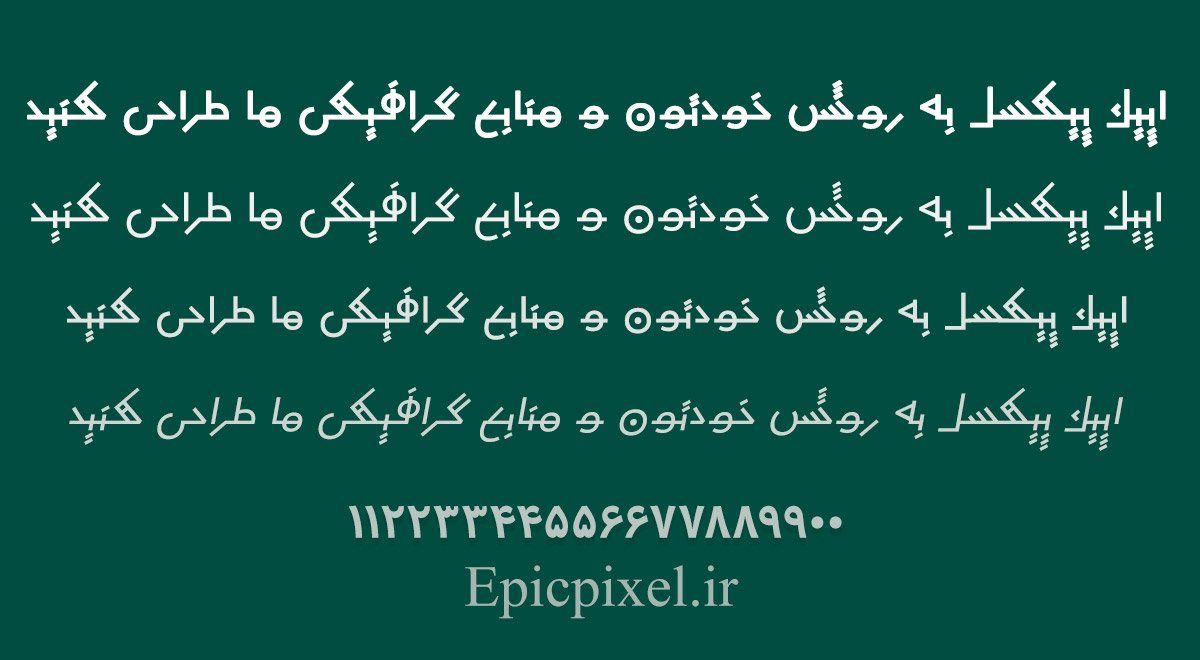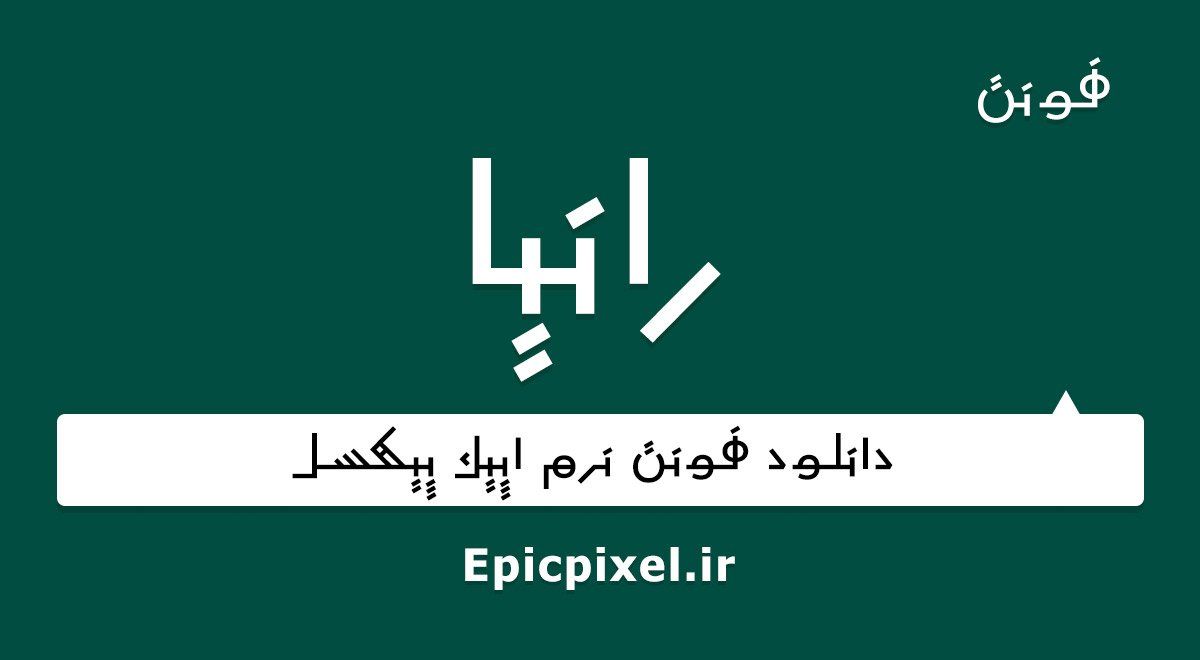
4 فونت رانیا فارسی Runya
فونت رانیا، با ظاهری مدرن و خاص، انتخابی ایده آل برای کسانی است که به دنبال تنوع و زیبایی در نوشته های خود هستند. این فونت رایگان، با خطوط باریک و ظریف خود، جلوه ای منحصر به فرد به متون می بخشد.
یکی از ویژگی های برجسته رانیا، نقطه های کشیده و مورب آن است که به نوشته ها حس پویایی و حرکت می بخشد و آنها را از حالت یکنواخت خارج می کند. این ویژگی به خصوص در طراحی های گرافیکی و عناوین جذابیت زیادی ایجاد می کند. تصور کنید عنوانی با این فونت، چقدر می تواند چشم نواز باشد!
البته باید به این نکته هم اشاره کرد که به دلیل ظرافت خطوط، ممکن است در اندازه های بسیار کوچک، خوانایی آن کمی کاهش یابد. بنابراین، توصیه می شود در متن های طولانی و با اندازه فونت کوچک، از فونت های دیگری که خوانایی بیشتری دارند، استفاده شود. اما در عناوین، پوسترهای تبلیغاتی، کارت ویزیت و طراحی های مشابه، رانیا بی نظیر است.
به طور خلاصه، اگر به دنبال فونتی مدرن، رایگان و با ویژگی های بصری خاص هستید که به نوشته های شما جلوه ای متفاوت ببخشد، فونت رونیا گزینه ای عالی است. این فونت با نقطه های کشیده و خطوط باریک خود، می تواند روح تازه ای به طراحی های شما ببخشد و آنها را جذاب تر کند.